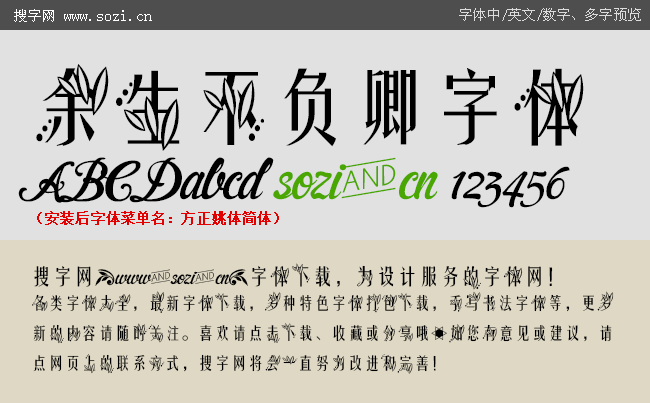
余生不負(fù)卿字體
搜字網(wǎng)給大家提供一款余生不負(fù)卿字體手機(jī)中文字體下載。這款手機(jī)字體是將方正姚體個(gè)別筆畫換成了卡通花紋圖案。方正姚體字體雋秀工整,結(jié)構(gòu)狹長(zhǎng),字間距較大,排印清晰,整齊劃一,被稱為“姚體”。加入了卡通圖案后又增添了趣味性,特別適合喜歡手機(jī)字體個(gè)性一些的朋友在手機(jī)上安裝使用。